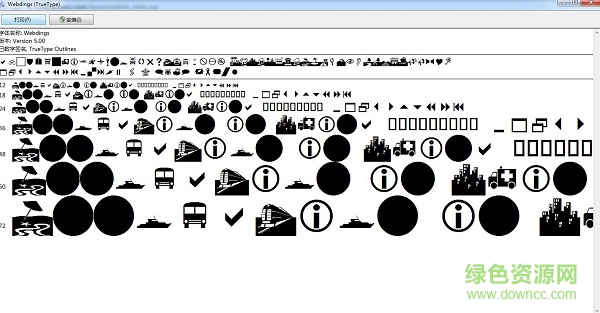
webdings是什么意思?webdings字體怎么用?webdings字體是一款特別的字體,每個(gè)字母和數(shù)字都代表不同的圖案,有對(duì)號(hào)、自行車、禮品包、公汽、救護(hù)車、飛行器等一系列圖案,按照以下方式安裝即可使用!
Webdings是一個(gè)TrueType的dingbat字體,于1997年發(fā)表,搭載在其后的Microsoft Windows視窗系統(tǒng)內(nèi),大多的字形都沒(méi)有Unicode的相對(duì)字。
其最大的特點(diǎn)就是它是由一種數(shù)學(xué)模式來(lái)進(jìn)行定義的基于輪廓技術(shù)的字體,這使得它們比基于矢量的字體更容易處理,保證了屏幕與打印輸出的一致性。同時(shí),這類字體和矢量字體一樣可以隨意縮放、旋轉(zhuǎn)而不必?fù)?dān)心會(huì)出現(xiàn)鋸齒。